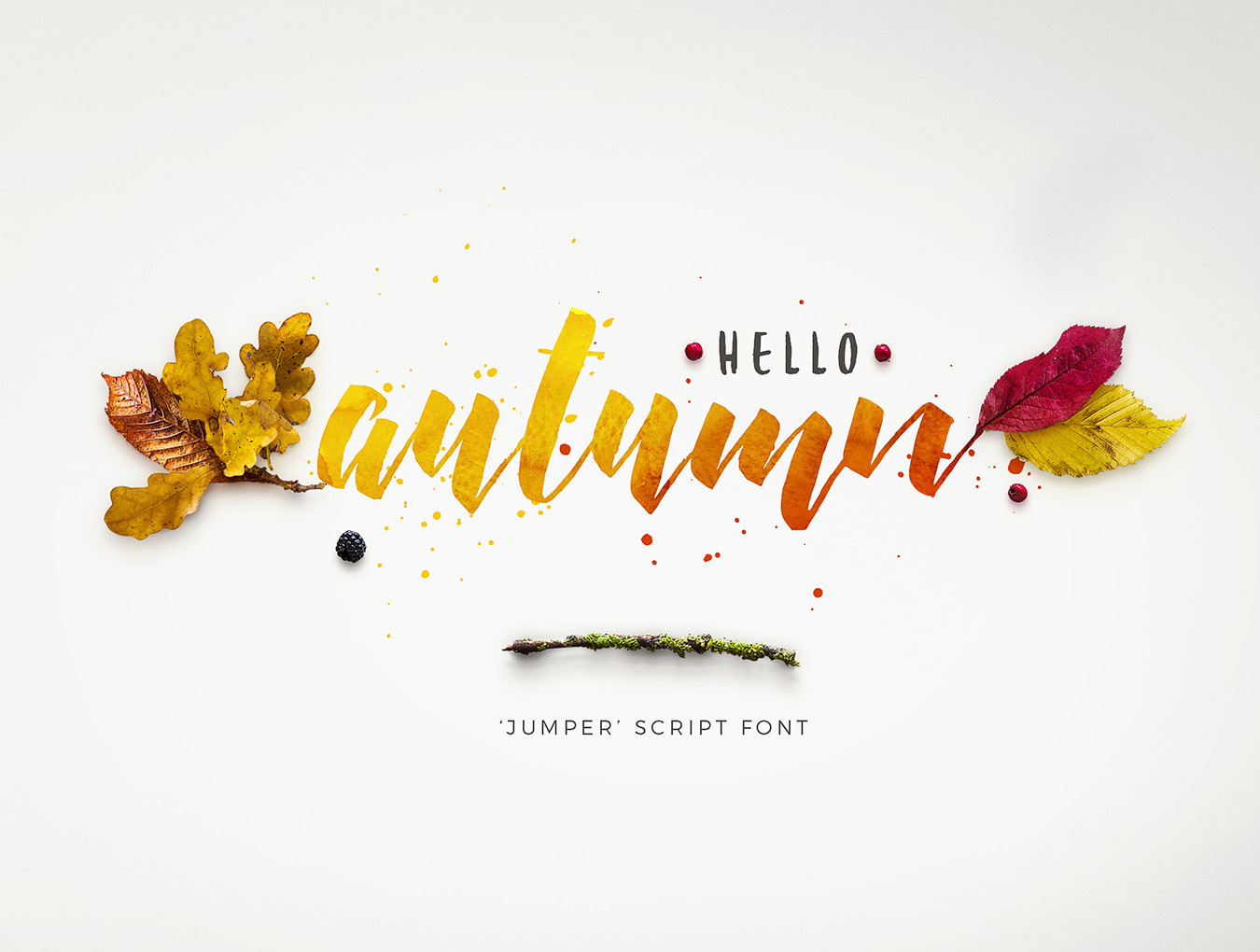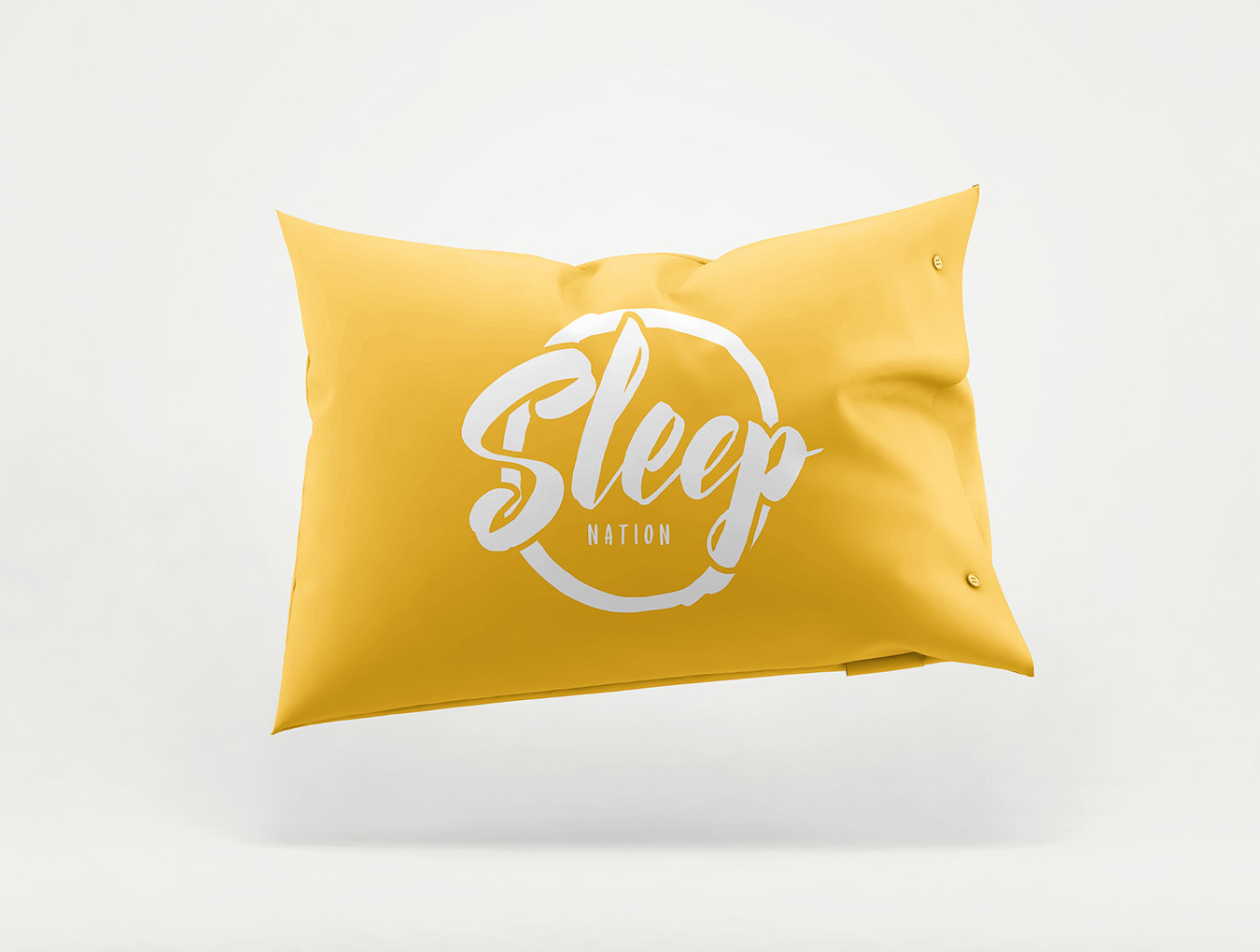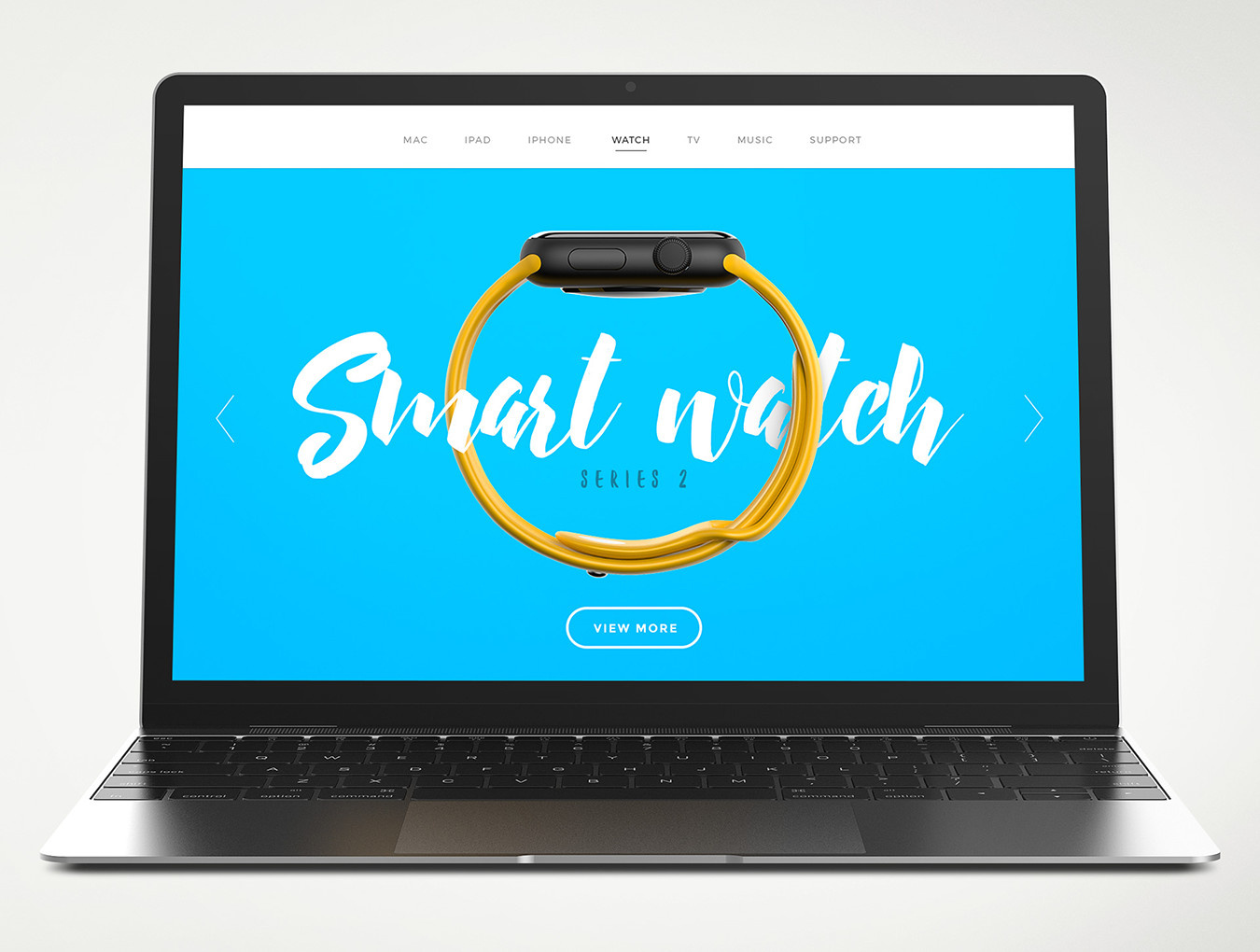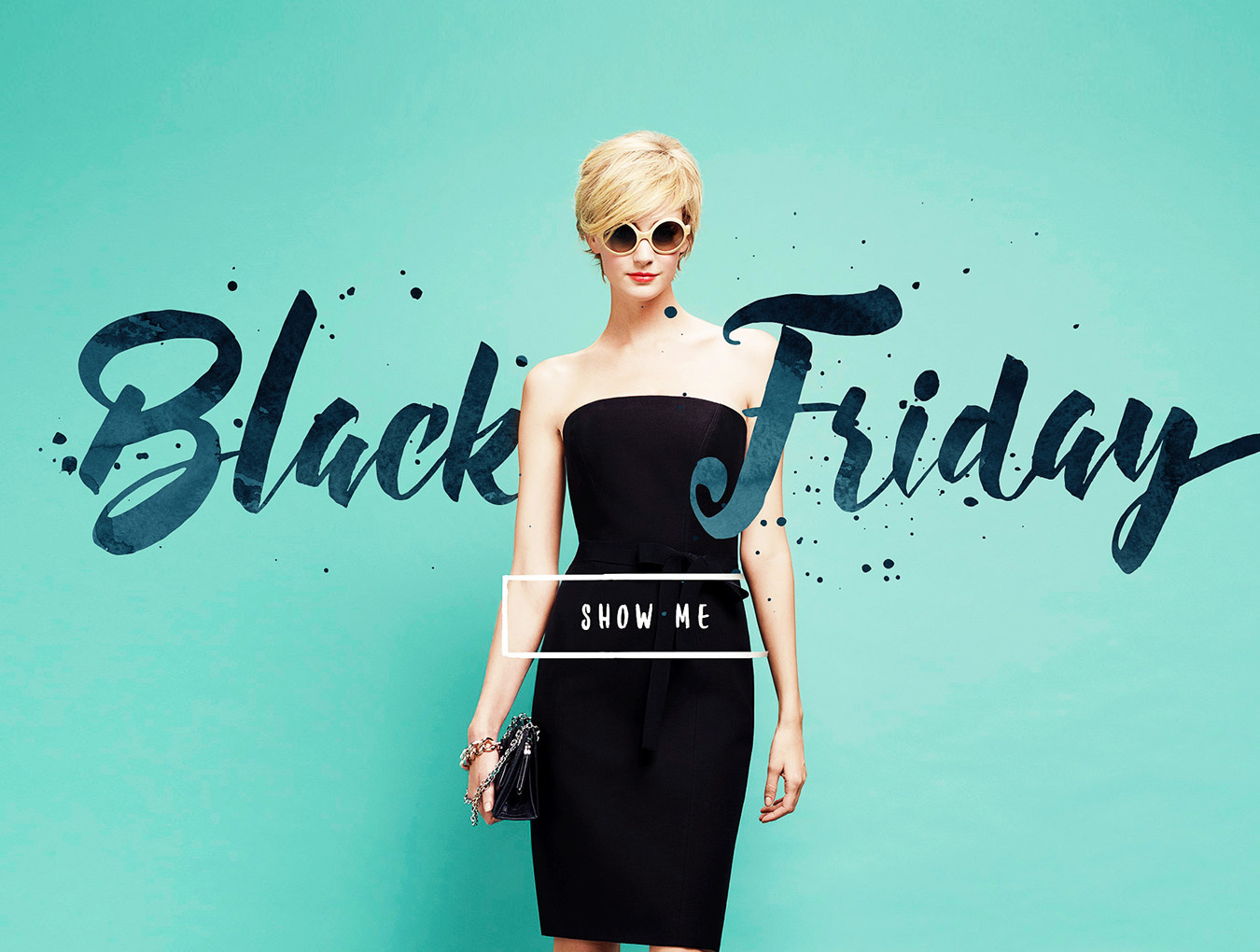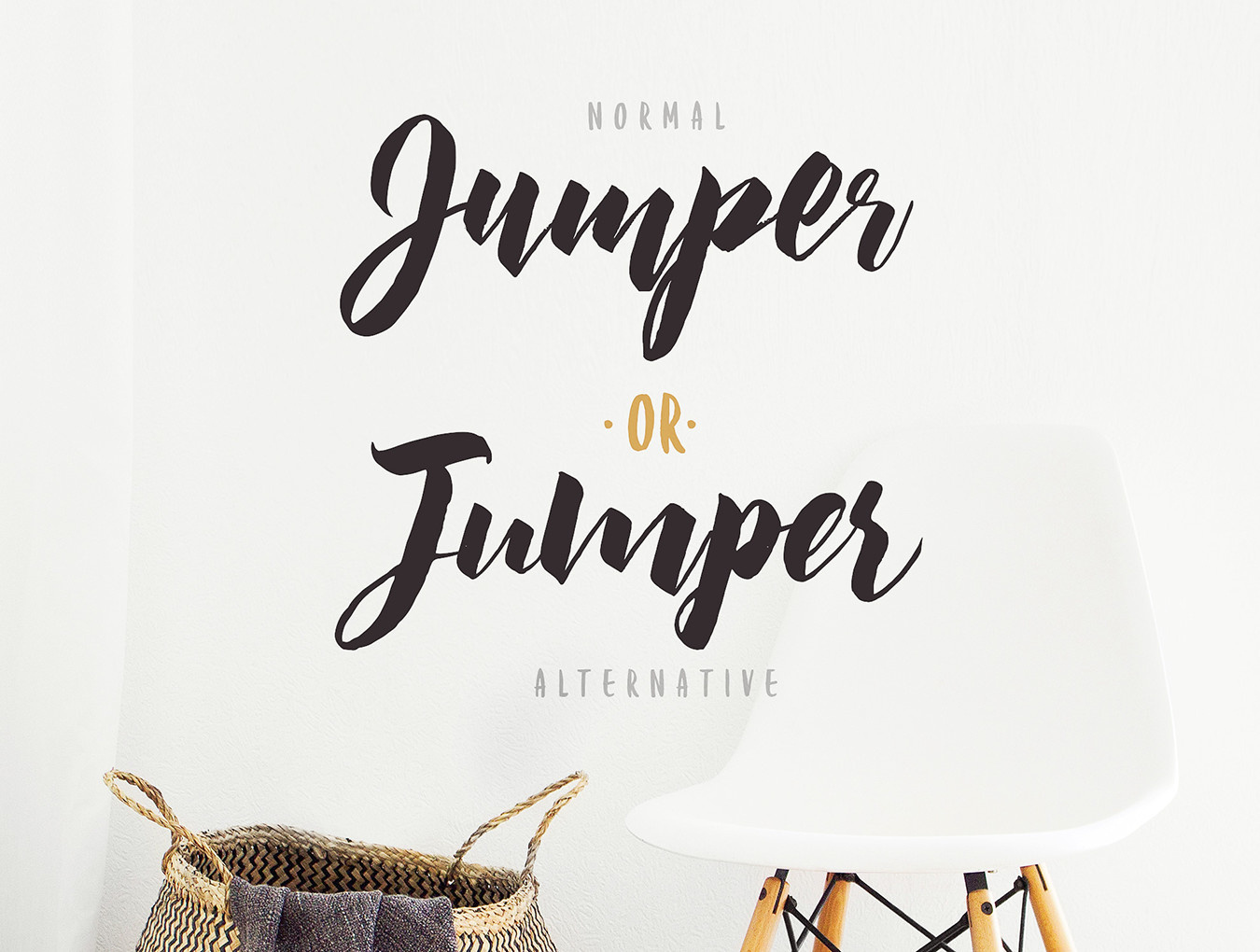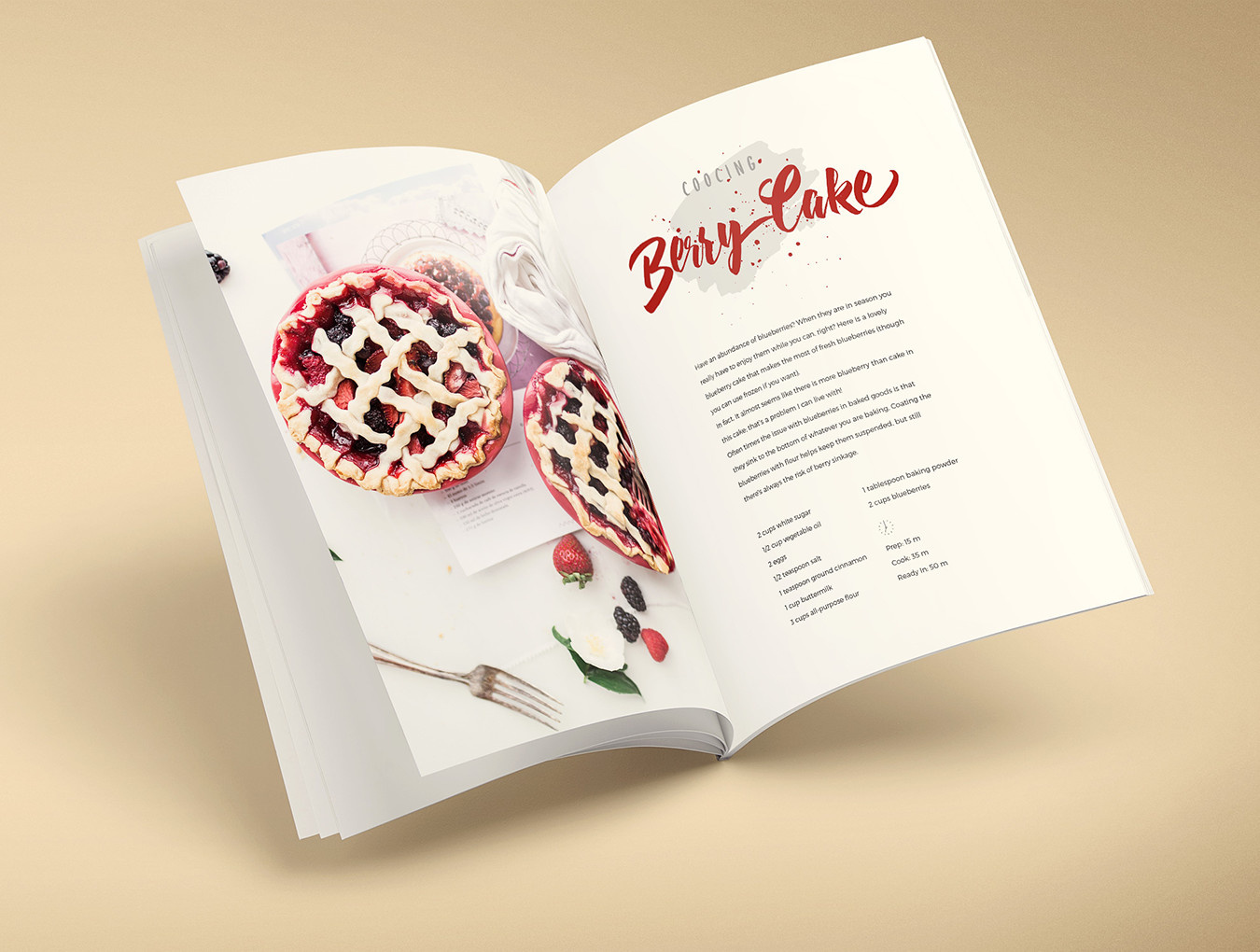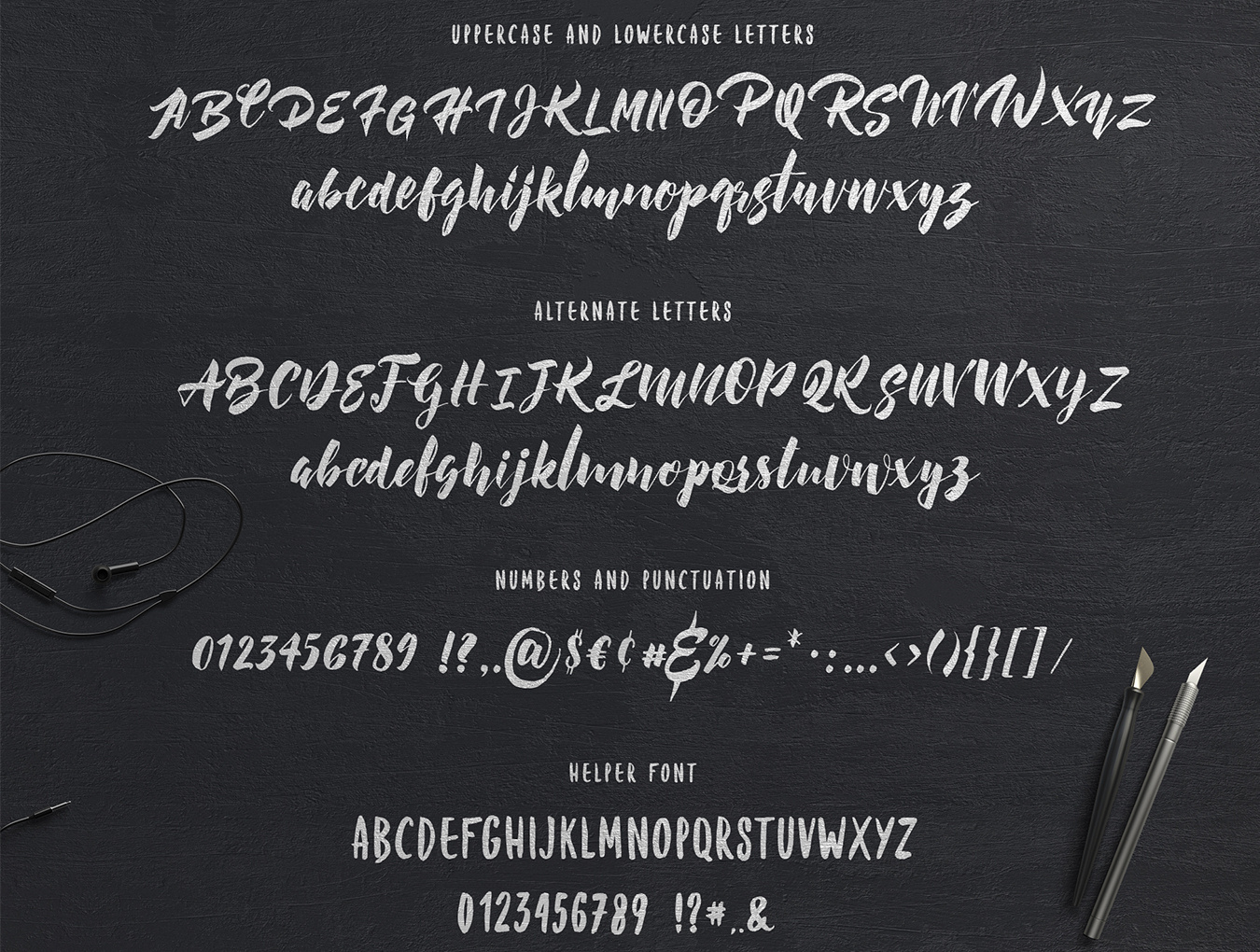
完美的脚本字体 - 爱你,跳线脚本字体
Perfect script font - with love for you, Jumper Script Font
Jumper是一种带刷子样式的OTF和TTF手工字体,非常适合信头,服装设计,标题,标识,海报,卡片等。对于拥有opentype功能软件的人来说:可以通过打开'在Photoshop的“角色”面板中或通过任何带有字形面板的软件上的文体交替'和'连字'按钮,例如Adobe Illustrator,Photoshop,Inkscape。